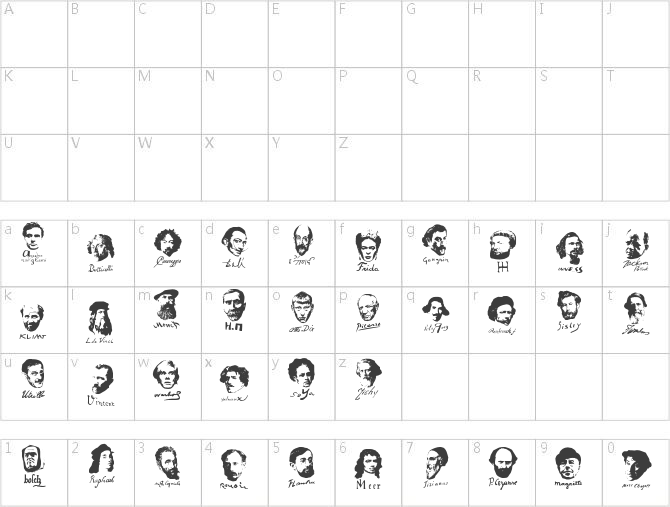
字體名稱: Thart_W
Thart_World_Painters
Thart_World_Painters介紹
Thart_World_Painters字體字庫是一款讓人賞心悅目、百看不厭的英文字體,適合各類廣告和產品包裝設計應用,字體大小0.18MB,格式為ttf字體,上傳用戶是gagilang,作者/版權方為未知